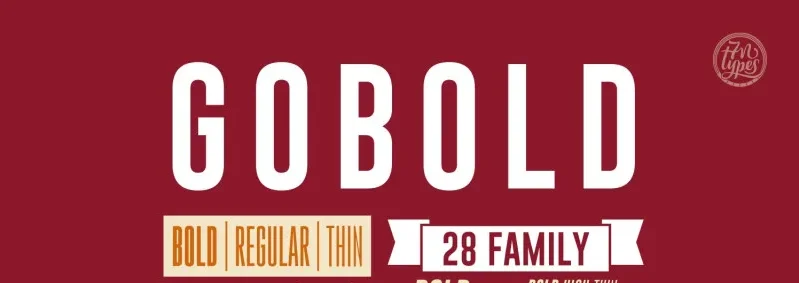
Tác giả: Situjuh Nazara
Phân loại: Hiện đại, Độc đáo
Gobold Font được thiết kế với những đường nét đậm, góc cạnh và cá tính, điều này khiến văn bản trở nên nổi bật và dễ dàng lôi cuốn người đọc. Phông chữ này, thuộc dòng font chữ không chân nên sẽ mang đến một cái nhìn hiện đại, táo bạo và đầy sức sống cho các tài liệu và thiết kế. Gobold Font phù hợp với các tiêu đề, logo, poster, banner và các ứng dụng yêu cầu sự chú ý mạnh mẽ. Một font chữ sở hữu đa dạng các phiên bản nên người sử dụng có thể dễ dàng kết hợp các phiên bản khác nhau để tạo ra những thiết kế ấn tượng và sáng tạo.